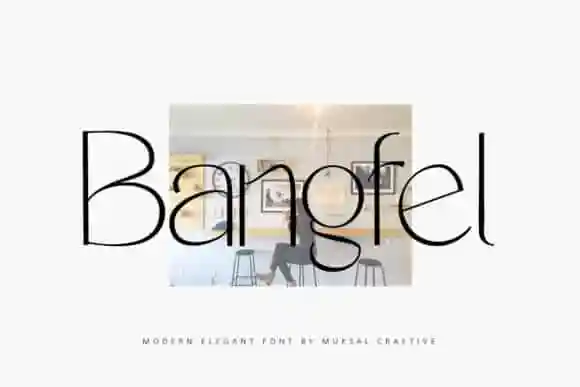
Bangfel Display Font – Fonte Grátis
Bangfel Display Font
Bangfel Display Font é uma elegante fonte sans serif que leva os designers a um futuro contemporâneo. Com seu estilo serif único, essa fonte traz uma sensação única aos caracteres minúsculos, equilibrando perfeitamente entre seriedade e suavidade. É de autoria do designer Muksal Creative, criado em um ambiente de design moderno e estiloso. O Bangfel Display Font possui um charme limpo, leve e fino que se assemelha a uma textura sedosa. Esta fonte está disponível no formato de download da 99designs, oferecendo um visual clean que é tanto memorável quanto estiloso. Seja para trabalhos profissionais ou criativos, o Bangfel Display Font traz seu próprio toque único e definitivo ao design. Este é um excelente recurso para quem procura uma fonte de qualidade para projetos visuais inovadores.